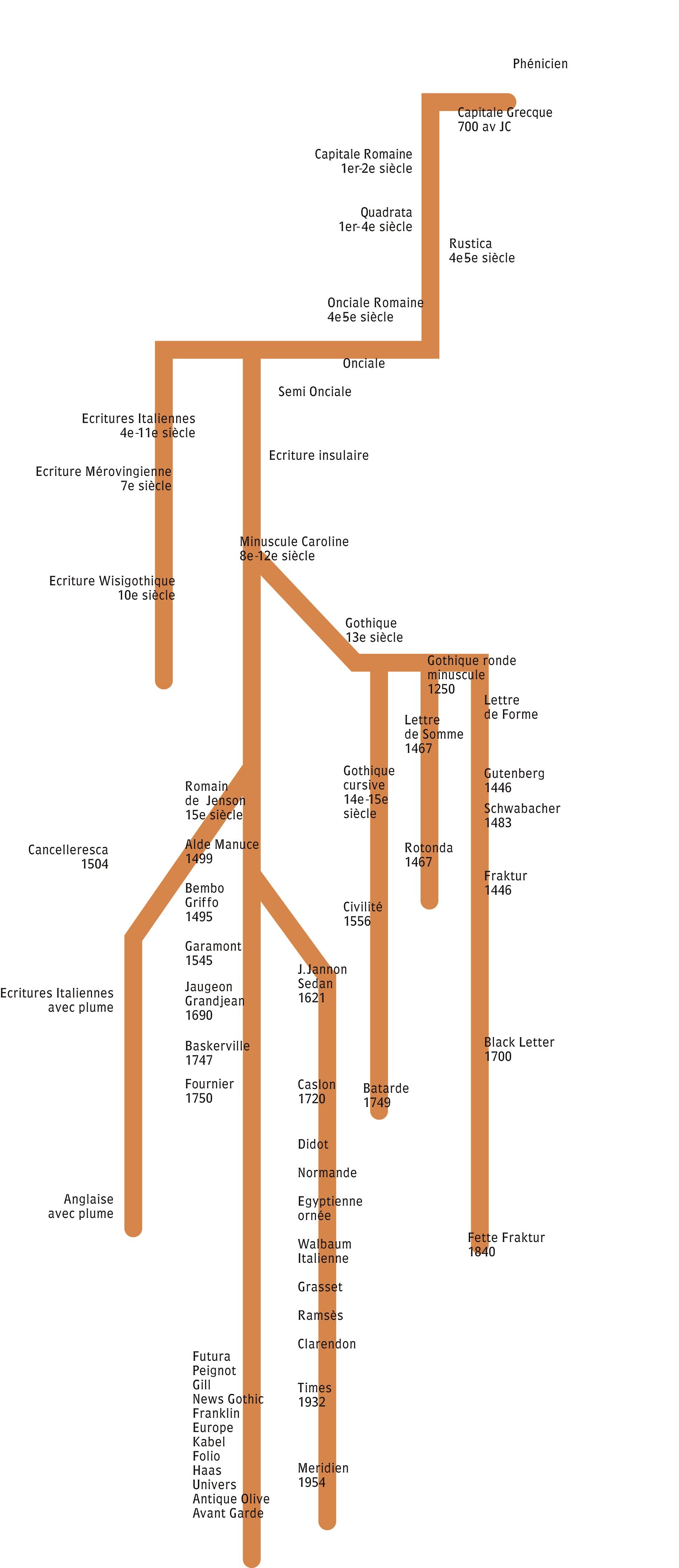
l’histoire de la typographie se confond avec celle de l’écriture de l’alphabet phonétique
suite du cours de typographie concernant la classification des caractères.
Comme vous avez pu le constater, plus on avance dans l’élaboration d’une histoire de la typographie, plus on cherche à affiner les filiations des caractères. Thibaudeau (1860-1925) a été longtemps la seule référence en France pour une classification des caractères d’imprimerie. Elzévirs, Didots, Bâtons, Egyptiennes. 4 formes alphabétiques de base pour déterminer le style et l’origine d’une police de caractère. Or notre connaissance de la chose imprimée n’a fait que s’affiner tout au long du XXe siècle de l’information. Comment peut-on classer un Bembo, un Garamont et un Times dans la même famille des Elzévirs. C’est pourtant ce que Thibaudeau nous propose. Et de regarder la forme des empattements, les contrastes des pleins et déliés, l’attaque de la partie supérieure d’un <a> bas de casse et l’on s’aperçoit tout de suite de différences notoires. Mais après-tout est-ce que cela sert à quelque chose de savoir classer les caractères?
Dans les années 50-90, pendant près de 40 ans nous avons été envahis dans toutes les agences de pub, de studio de réalisations graphiques par les catalogues de caractères, tels que celui-ci dessous…
extrait d’un catalogue «Type Book» typoGabor (1988)
Bien avant l’arrivée des Macintosh et des technologies typographiques vectoriels, les ateliers de composition proposaient à leurs clients d’innombrables formes alphabétiques dans des dizaines de catalogues mis à la disposition des directeurs artistiques des agences. Pour s’y retrouver une seule solution, avoir une connaissance intime de la forme des alphabets afin de «pressentir» à l’avance ce qu’on y cherchait. De savoir reconnaître une Elzévir d’une Egyptienne ne suffisait plus. Et Maximilien Vox, fondateur des rencontres graphiques de Lure l’avait bien compris. A l’instar de Giono qui avait créé les rencontres du Contadour, Vox va se réunir avec quelques amis, Jean Garcia, John Dreyfus et plus tard François Richaudeau, Charles Peignot, Roger Excoffon sur les hauteurs du village de Lurs en Provence afin de tenter de jeter les bases d’une réflexion moderne sur la typographie. C’est ainsi que naîtra la Classification Vox qui recueille aussitôt l’assentiment de l’Association Typographique Internationale. Les Elzévirs sont éclatés en 3 familles, les Humanes, les Garaldes et les Réales. Ce que les Américains jettent pêle-mêle dans une seule catégorie «Old Style» (sans doute Old Style pour tout ce qui précède la naissance des États-Unis), mais avant d’aller plus loin dans cette affaire de classification je vous emmène faire un flash-back sur l’histoire de l’écriture. Ci-dessous un tableau simplifié qui résume la filiation des écritures depuis 700 av JC :
Bien sûr nous savions que les caractères bâtons, Linéales chez M.Vox n’étaient en rien modernes. Ils ont été tracés, bien avant l’alphabet grec ou phénicien (700 av JC) sur les inscriptions cunéiformes véritable proto-alphabet de celui phonétique qui nous vient tout droit des phéniciens. Mais il est toujours intéressant de rappeler un contexte. C’est celui du support, et de l’outil. Les lettres tracés à l’aide d’une pointe sur une pierre argileuse ou de la cire ne ressemblent en rien aux lettres que les romains nous laissèrent sur la colonne Trajane. Eux se servaient de ciseaux pour tailler la pierre… Remarquez ci-dessus l’élégance des lettres A grecs et la régularité du tracé sur les pierres. (images cliquables).
A peine quelques centaines d’années s’écoulent, 200-300 et nous sommes plongés au cœur de la cité antique romaine qui pratique l’écriture comme moyen politique autant qu’artistique.
Les formes s’affinent, au croisement des tailles de ciseaux, un léger empattement «incise» apparaît, ce qui permit à M.Vox d’installer cette Classe des Incises juste avant les Humanes. On dira aussi des caractères lapidaires, provenant des inscriptions sur les pierres tombales ou les frontispices des monuments romains. Cependant les choses vont très vite.
Les hommes s’adaptent, taillent des plumes (calame) pour en tremper le bout dans une encre et tracer les lettres sur un épais parchemin. La souplesse du poignet, la vélocité de la main qui parcourt une feuille posée sur la tablette du script (scriptorium) entraîne rapidement à des modifications magistrales dans les formes alphabétiques.
l’attaque du plat de la plume sur le papier entraîne ipso-facto la naissance des pleins et déliés, mais il faudra attendre le Moyen Âge, l’époque de Charlemagne vers le 8e-9e siècles pour que l’Onciale se voit tracer avec des lettres hybrides d’abord, on dirait aujourd’hui des bas de casses capitalisées ou petites capitales, qui deviennent progressivement des minuscules (puisque la casse de Gutenberg ne verra le jour que vers 1450). La minuscule carolingienne ou caroline représente parfaitement l’ancêtre de nos écritures d’imprimerie moderne.
Parallèlement nous voyons déjà clairement apparaître les fondamentaux de la mise en page Gutenbergienne. Titres, Lettrines, vignettes décoratives.
Qui ne se souvient de cette scène du Nom de la Rose où des dizaines de moines traçaient les parchemins debout devant l’écritoire… Ainsi il faut toujours se souvenir qu’avant la lettre d’imprimerie, la lettre fut tracée, travaillée selon des techniques calligraphiques de plus en plus raffinées. La gymnastique du poignet se codifiant avec l’expérience des Jan van De Velde, ancêtre de nos calligraphes modernes dont un des plus talentueux descendants Claude Fernand Mediavilla fréquenta l’école de Bernard Aarin, le Scriptorium de Toulouse. Mais je m’avance un peu trop vite, nous ne sommes qu’à l’aube de l’ère du caractère Gothique.
Référence bibliographique : Il s’agit de l’extraordinaire ouvrage de Roger Druet et Herman Gregoire préfacé par Roland Barthes et François Richaudeau (publié chez Artheme Fayard & Dessain et Tolra en 1976 – édition épuisée) : La Civilisation de l’Écriture.